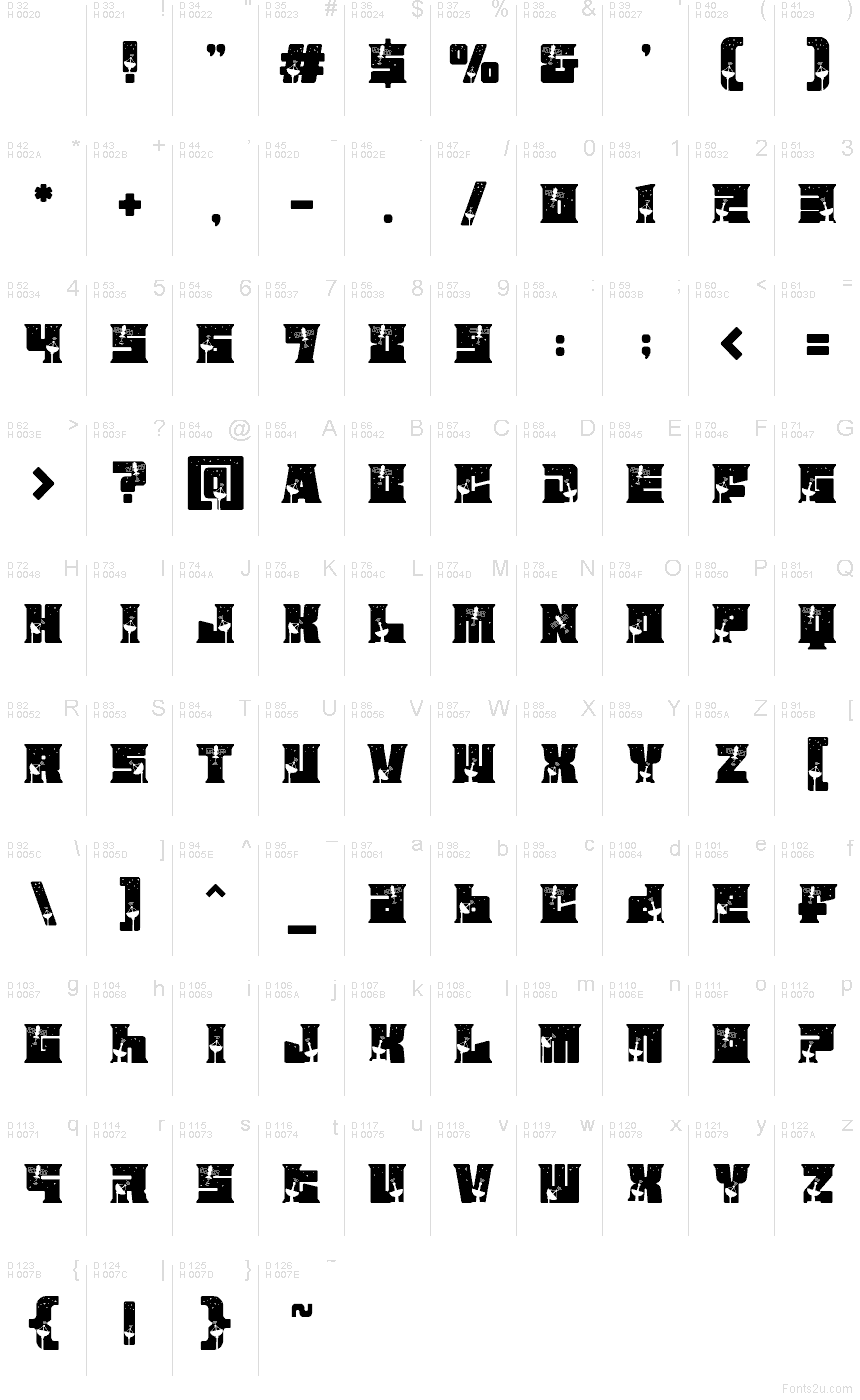
Astral Zenith Four od Putracetol Studio je bezplatné písmo typu display s vesmírnou tematikou. Tvoří ho robustní znaky doplněné observatořemi, satelitními talíři a drobnými hvězdnými poli. Opakující se výřezy dodávají designu plakátový nádech, takže každé písmeno působí spíše jako kousek astronomického vybavení nebo architektury než jako obyčejné písmo.
Díky tomu je přirozenou volbou pro sci-fi titulky, plakáty astronomických klubů, letáky do planetárií, grafiku pro akce zaměřené na STEM či tematické obaly. Protože jsou vesmírné motivy včleněny přímo do tvarů písmen, a ne jen jako samostatné ikony, může Astral Zenith Four vyniknout i v náhledech videí nebo ve výukových materiálech pro děti, kde musí být téma patrné na první pohled.
Astral Zenith Four